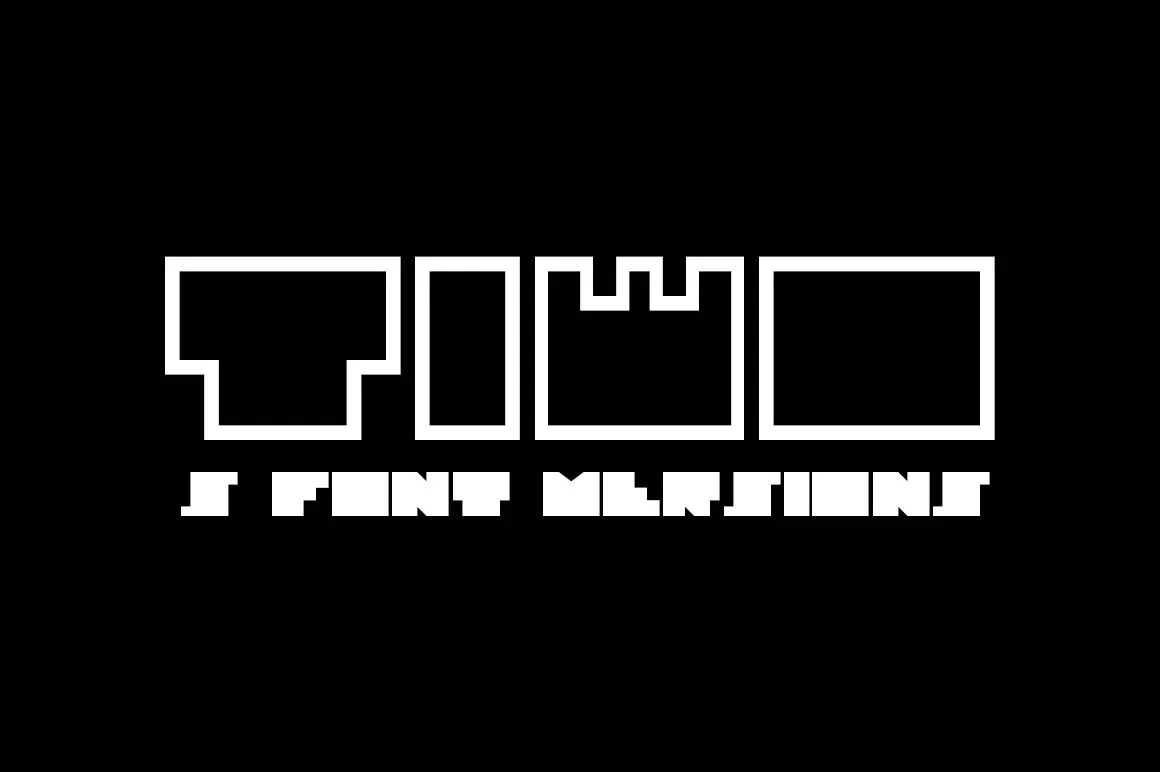
Tiwo Display Font – Download Grátis
Introduzimos uma nova fonte de display chamada Tiwo Display Font. Desenvolvida e compartilhada de graça pela Alt Type Foundry, essa fonte é perfeitamente destinada a ambientes de uso publicitário ou para gráficos impactantes. Tiwo foi criada com linhas muito agressivas e afiadas, ideal para aplicação em displays, ilustrações, painéis informativos, logotipos, roupas personalizadas, títulos e muito mais. Seja você um designer de gráficos ou criativo, Tiwo está aqui para tornar seus projetos ainda mais impactantes e chamativos.